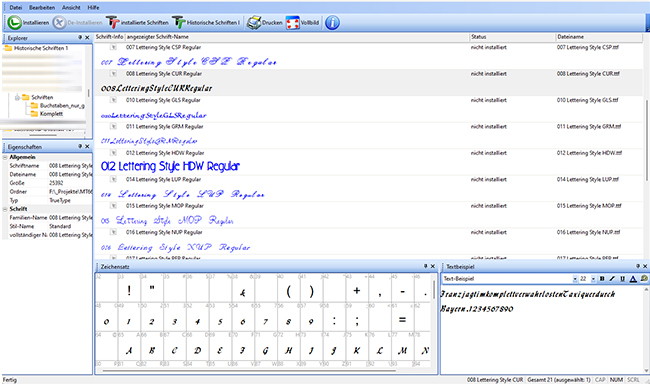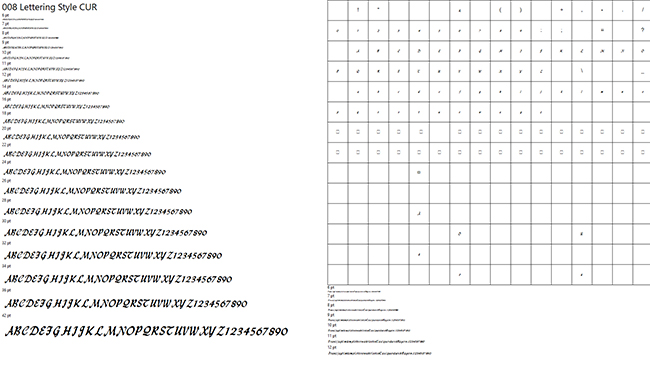
Historische Schriften 1
- Gestalten und Drucken wie ein Profi!
- Druckstücke mit dem ganz besonderen Flair
Tauchen Sie ein in die Vergangenheit mit unserer exklusiven Sammlung historischer Schriftarten
Erwecken Sie Ihre Designs zum Leben und verleihen Sie ihnen einen Hauch von Nostalgie mit unserer umfangreichen Sammlung an historischen Schriftarten.
Die "Historische Schriften I" bieten eine sorgfältig kuratierte Auswahl an Schriftarten, die von vergangenen Epochen und stilistischen Strömungen inspiriert sind, und ermöglichen es Ihnen, Ihren Projekten einen unverwechselbaren und künstlerischen Charakter zu verleihen.
Ob für eine Urkunde, für eine pfiffige Einladungskarte oder für eine Geburtstagszeitung. Mit diesen, großteils von Mönchen handgezeichneten Schriften verleihen Sie Ihren Druckstücken einen ganz besonderes edlen Look.
Entdecken Sie weitere spannende Anwendungen!
Unsere "Historische Schriften" bieten Ihnen nicht nur die Möglichkeit, Ihren Designs einen Hauch von Geschichte zu verleihen, sondern eröffnen auch ein Meer an kreativen Möglichkeiten für Spaß und Unterhaltung.
Authentizität zu verleihen: Verleihen Sie Ihren Projekten mit Schriftarten, die von vergangenen Äras inspiriert sind, eine authentische und unverwechselbare Ästhetik.
Cosplay-Abenteuer intensivieren: Tauchen Sie tiefer in die Welt des Cosplays ein, indem Sie authentische Briefe und Dokumente im Stil vergangener Zeiten erstellen, die Ihren Charakteren zusätzliche Tiefe und Authentizität verleihen.
Uralte Schatzkarten gestalten: Kreieren Sie einzigartige Schatzkarten im Stil vergangener Epochen, um die Spannung und den Nervenkitzel von Geburtstagsfeiern und anderen Veranstaltungen zu steigern und Ihren Lieben unvergessliche Abenteuer zu bereiten.
Ritterturniere und mittelalterliche Feste bereichern: Nutzen Sie die künstlerischen Schriftarten, um Einladungen, Ankündigungen und andere Druckerzeugnisse für Ritterturniere, mittelalterliche Feste und ähnliche Veranstaltungen zu gestalten, und schaffen Sie so eine faszinierende und authentische Atmosphäre für Ihre Besucher.
Eine nostalgische Atmosphäre zu schaffen: Erschaffen Sie eine nostalgische Stimmung und transportieren Sie Ihre Leser oder Betrachter in vergangene Zeiten, indem Sie Schriftarten verwenden, die das Flair vergangener Epochen einfangen.
Einzigartigkeit zu betonen: Heben Sie sich von der Masse ab, indem Sie Schriftarten verwenden, die eine künstlerische Raffinesse und eine reiche Geschichte vermitteln, und dadurch Ihre Botschaft oder Ihr Design noch stärker betonen.
Experimentieren Sie mit einer Vielzahl von Schriftarten, die von verschiedenen historischen Perioden inspiriert sind, um eine breite Palette an kreativen und faszinierenden Designs zu gestalten, die Ihre Zielgruppe begeistern werden.
Unsere "Historische Schriften I" sind ein unverzichtbares Werkzeug für Grafikdesigner, Werbefachleute, Kreative und alle, die ihre Projekte mit einem Hauch von Geschichte und Kultur bereichern möchten.
Verleihen Sie Ihren Kreationen eine zeitlose Eleganz und eine reiche kulturelle Dimension mit unserer Sammlung an historischen Schriftarten.